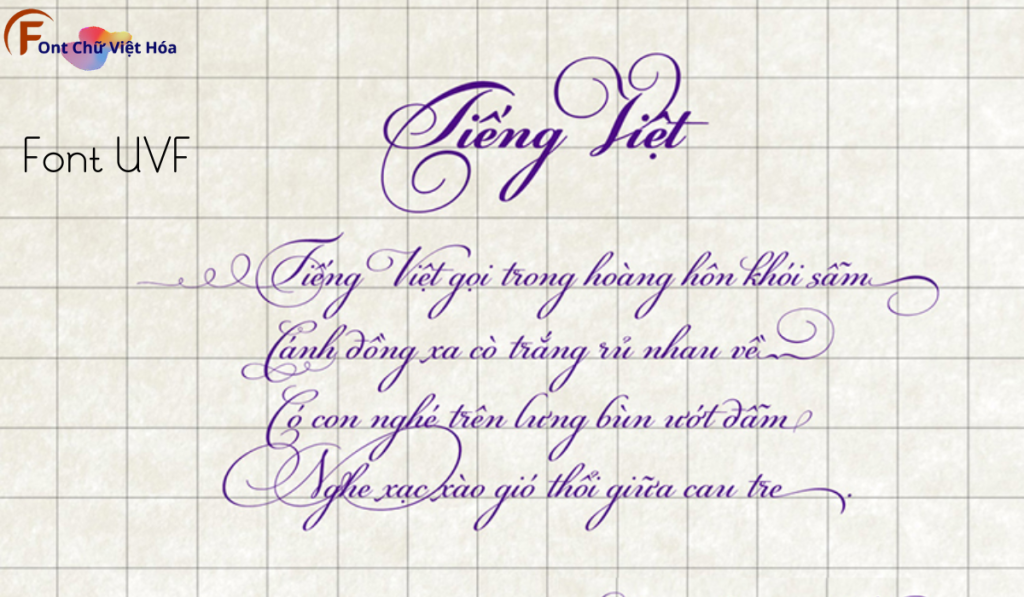
Font UVF Champion Script Pro Việt Hóa
Tác giả: Champion Type
Bộ Font: UVF
Kiểu chữ: Chữ viết tay
UVF Champion Script Pro Việt Hóa là font chữ thảo với các đường nét mềm mại và tinh tế, thuộc bộ font UVF. Font này được thiết kế nhằm mục tiêu tạo ra sự thanh lịch và dễ đọc, đặc biệt phù hợp cho các thiết kế như thiệp mời, poster, và logo. Đặc điểm hình dạng của UVF Champion Script Pro là các đường nét uốn lượn và tỷ lệ chữ cân đối, giúp tạo ấn tượng thị giác mạnh mẽ. Font này cũng đã được Việt hóa, mang đến sự linh hoạt và tiện dụng cho các dự án thiết kế bằng tiếng Việt, giúp người dùng dễ dàng tiếp cận và sử dụng.